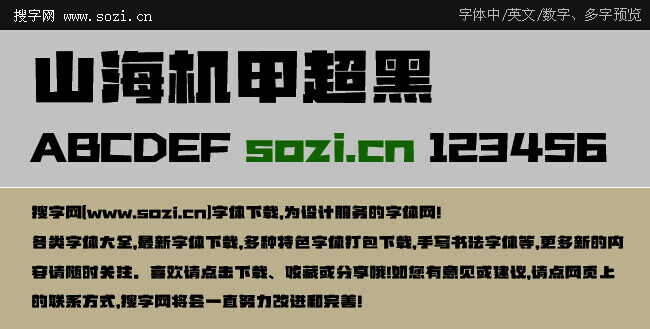
山海機(jī)甲超黑
搜字網(wǎng)提供一款山海機(jī)甲超黑中文藝術(shù)字體下載,山海機(jī)甲超黑是一款綜藝標(biāo)題黑體字體,包含簡(jiǎn)體漢字6763個(gè)。該字體是一款具有強(qiáng)勁視覺沖擊力的綜藝風(fēng)格標(biāo)題字體。字形寬大扁平,充實(shí)填滿整個(gè)字框,造型硬朗,全直線的筆畫構(gòu)成棱角分明、堅(jiān)實(shí)有力。適合包裝設(shè)計(jì)、海報(bào)設(shè)計(jì)、廣告設(shè)計(jì)等應(yīng)用。